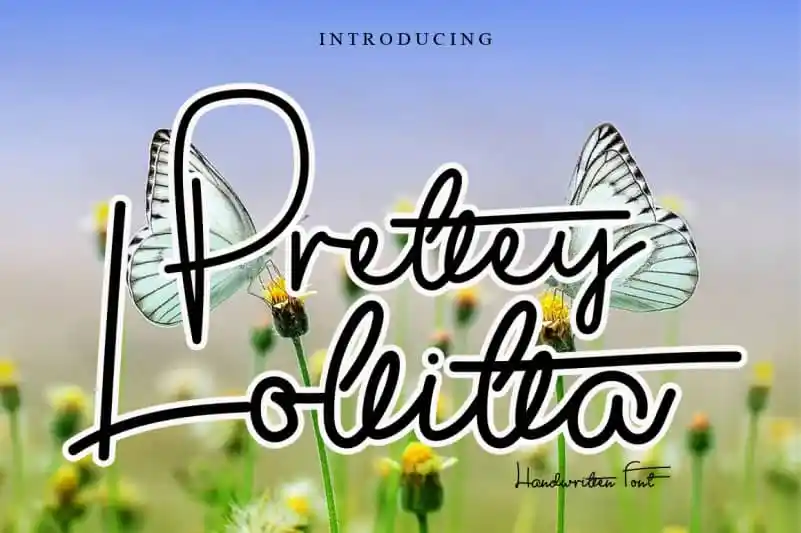
Pretty Lollitta Font – Download Grátis
A Pretty Lollitta Font é uma tipografia escrita a mão simples, fina e doce, perfeita para projetos que buscam uma sensação delicada. Com seu caráter versátil, essa fonte enriquece um amplo leque de ideias gráficas, elevando-os para um novo patamar. Ideal tanto para texturas românticas quanto para designs minimalistas modernos, ela oferece flexibilidade para adaptar-se a diversas necessidades criativas. Como uma amiga confiável, Pretty Lollitta Font é perfeita para quem busca uma fonte escrita à mão com um toque delicado e sofisticado que se adapta ao seu estilo único de design.